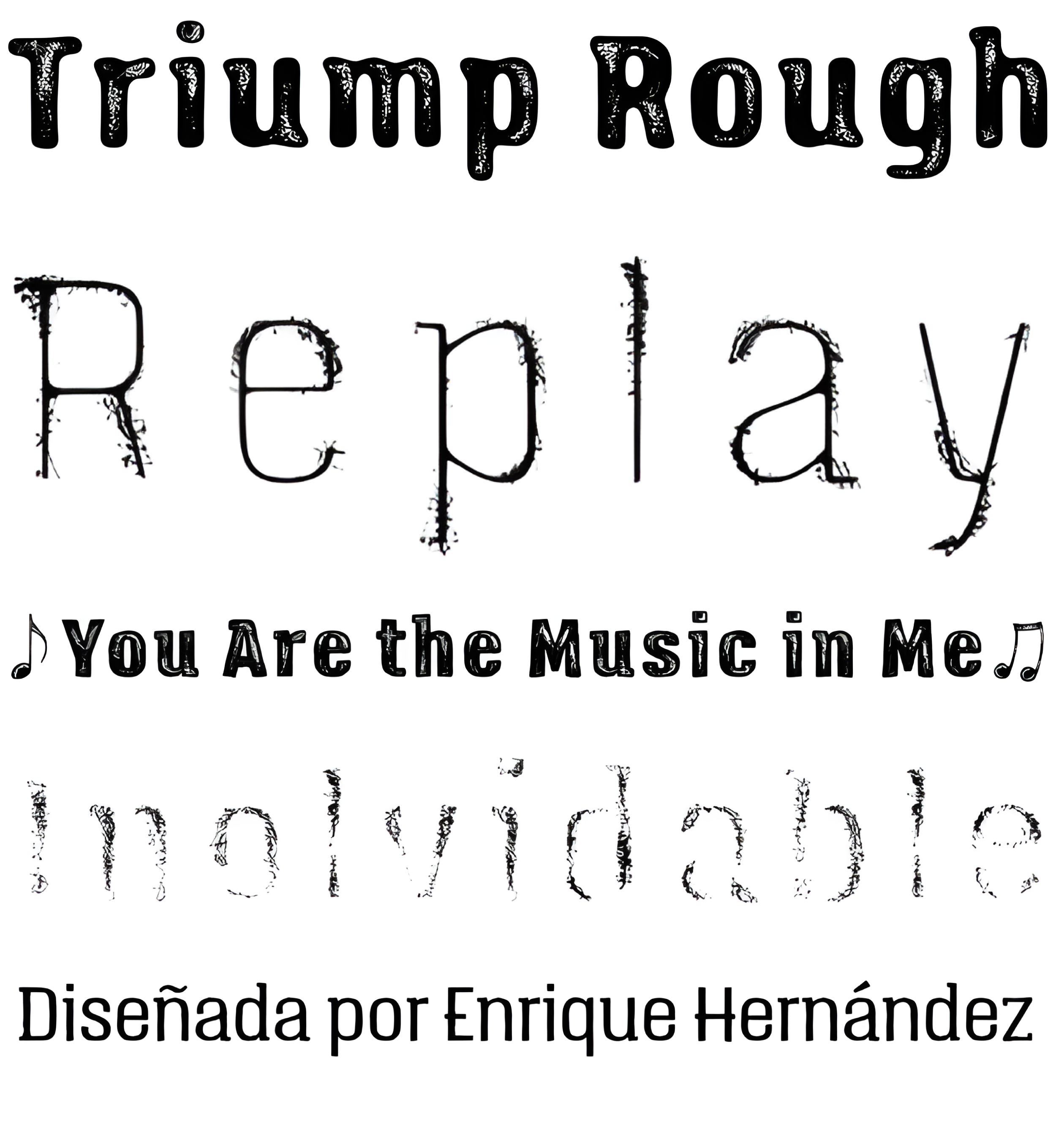
| Descripción | El tipo de letra Triump Rough viene con 2 subfamilias diferentes: Blur, una fuente suave y delicada con un aire vintage y hipster que da un soplo de aire fresco a su diseño; y Rock, una fuente fuerte y dura en mayúsculas y minúsculas muy adecuada para titulares de gran impacto. Esta versión ofrece una amplia variedad de características OpenType, como ligaduras, alternativas y palabras clave, así como una serie de adornos y extras, que ayudan a dar un aspecto diferente a sus ilustraciones. |
| Clasificación | Títulos, Dingbats |
| Familia(s) | Blur-01, Blur-02, Blur-03, Blur-04, Blur-05, Blur-06- Blur-07, Blur-08, Blur-09, Blur-10, Blur-11, Blur-12, Rock-01, Rock-02, Rock-03, Rock-04, Rock-05, Rock-06, Rock-07, Rock-08, Rock-09, Rock-10, Rock-11, Rock-12, Ornaments, Extras |